字语字库“咏”字系列,经典回顾~
匠心创作,一笔一划勾勒汉字之美,字字倾心,笔锋错落间独显气质。
字语咏楷体设计源于赵体楷书,保留了赵体跳跃的点画,率意自然的连带,弹性十足的劲道,对笔形进行了重新设计和规范,增强了字体的统一度,既保留传统的书写韵味,又符合现代排版和正文的诉求,丰富现有楷体数量,适用于书籍、报纸、屏显、包装广告、游戏等场景。
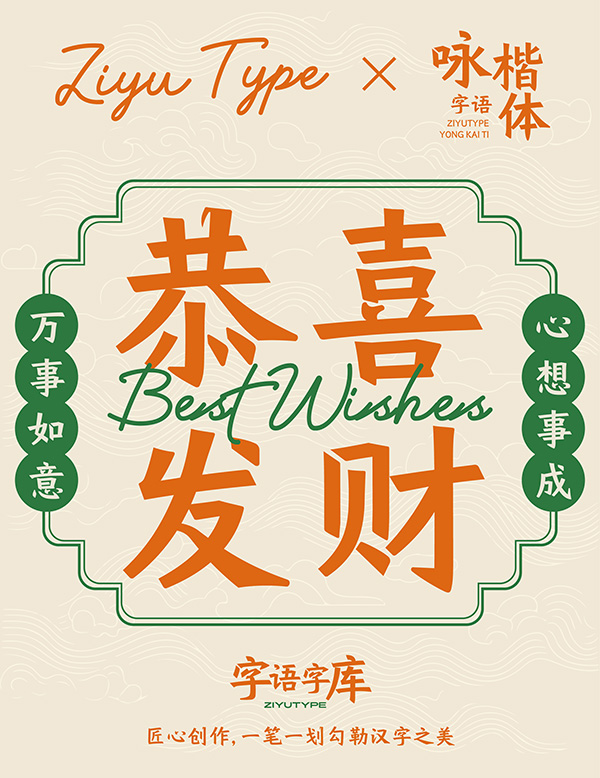
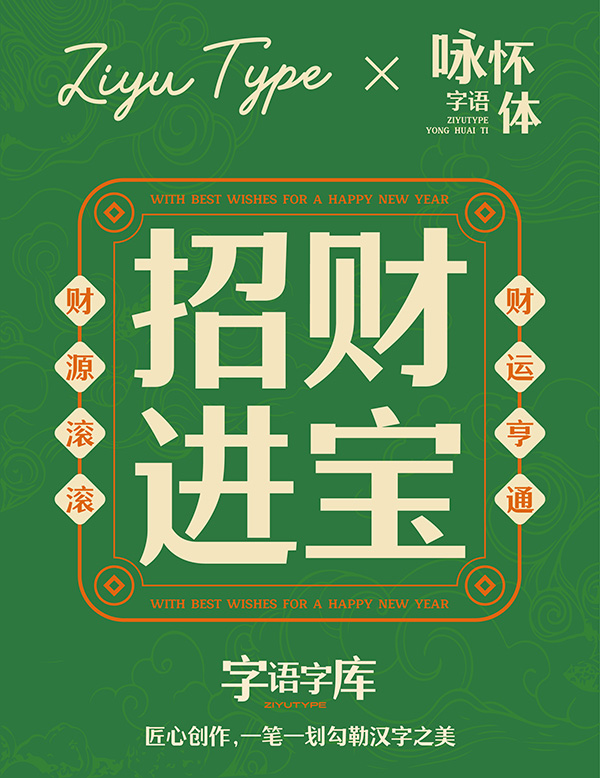
字语咏宏体笔画由粗壮的几何直线构成,负形平行、对称,重心平稳,字面饱满。风格时尚、刚正、厚重,分量感十足。该款字体设计感强,个性时尚,适用于标题显示及男性商业品牌的广告、产品包装设计和影视作品。
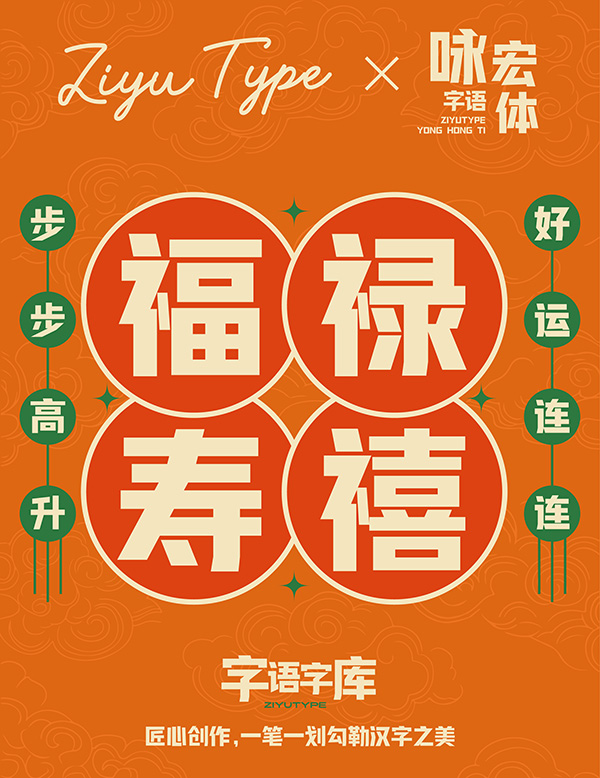
字语咏宋体的设计是一种大胆的尝试,把横画的衬线去掉,弱化撇捺起笔的笔锋,保留勾和转折处的特点;整体字势向右上,符合右手书写的习惯;在点画造型上追求简洁明了、俊秀刚劲,阅读舒适,适用于书籍、正文、标题、屏显等场景。
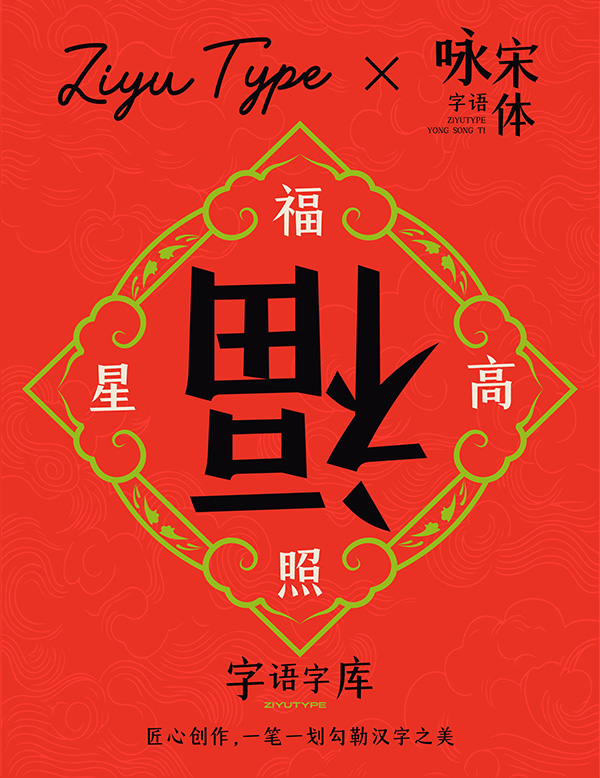
字语咏尚体其结构上加入了黑体的韵味,整体粗细均匀,“点、撇、捺、勾”的收笔为垂直切;文字轮廓兼具几何形态,简洁理性。适用于活动宣传、文艺杂志、综艺影视、广告以及品牌包装等场景。